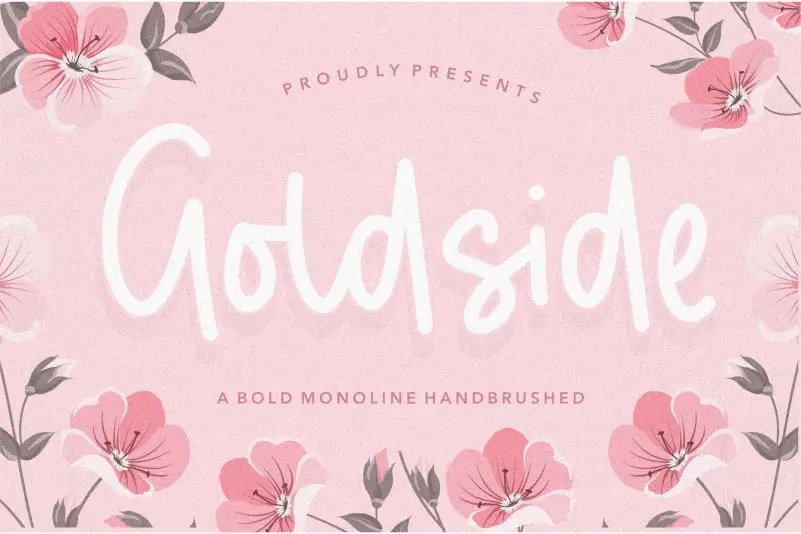
Goldside Bold Monoline Handbrushed Font – Download Grátis
A fonte Goldside Bold Monoline Handbrushed é perfeita para os projetos mais criativos do seu portfólio. Com sua caligrafia suavizada e linha única, ela oferece um estilo único que se destaca de entre as demais. Este recurso script é ideal tanto para aplicação em embalagens de produtos, criação de marcas e revistas, como também para mensagens a serem destacadas em redes sociais ou até mesmo para assinalar textos acima de imagens de fundo. Seja para anunciar o lançamento de um produto inovador ou criar uma identidade visual exclusiva para sua próxima campanha de wedding planner, Goldside é a escolha perfeita para expressar seu design no nível que desejar. Com suas linhas elegantes e textura única da caligrafia manuseada, este recurso script adquirirá um toque único e sofisticado ao decorar sua próxima publicação.